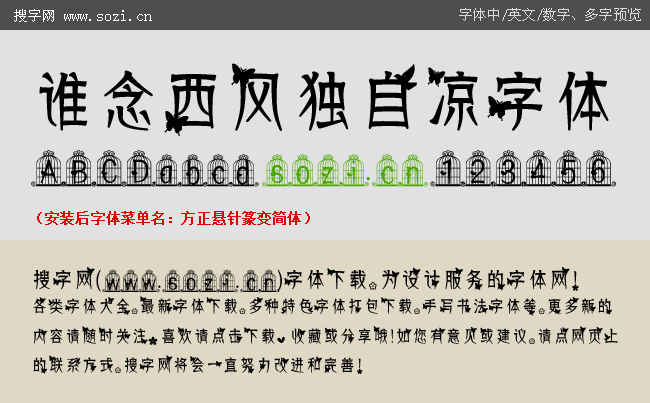
誰念西風(fēng)獨自涼字體
搜字網(wǎng)給大家提供一款誰念西風(fēng)獨自涼字體手機中文字體下載。這款手機字體是在方正懸針篆變簡體筆畫間插入了卡通圖案。方正懸針篆變字體意在保留篆書韻味,同時將隸書與楷書筆畫特征熔于一爐,實為三種書體的統(tǒng)一。將傳統(tǒng)書法藝術(shù)與現(xiàn)代形式語匯融合,追求裝飾性及藝術(shù)美感,端莊秀美、開張疏朗,雍容大氣、復(fù)古卻易讀。加入了卡通圖案后又增添了趣味性,特別適合喜歡手機字體個性一些的朋友在手機上安裝使用。